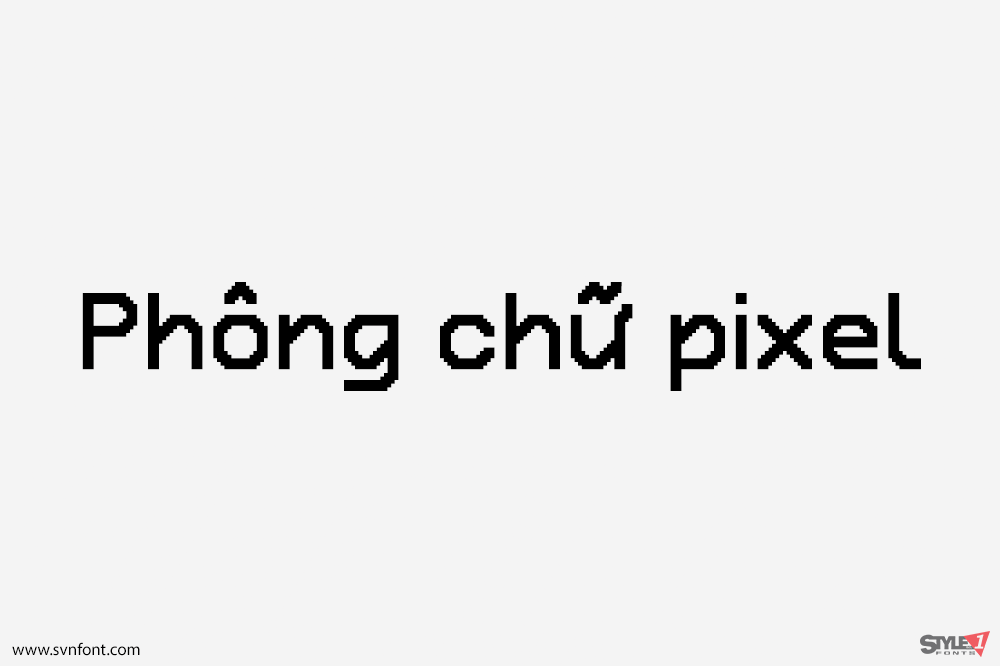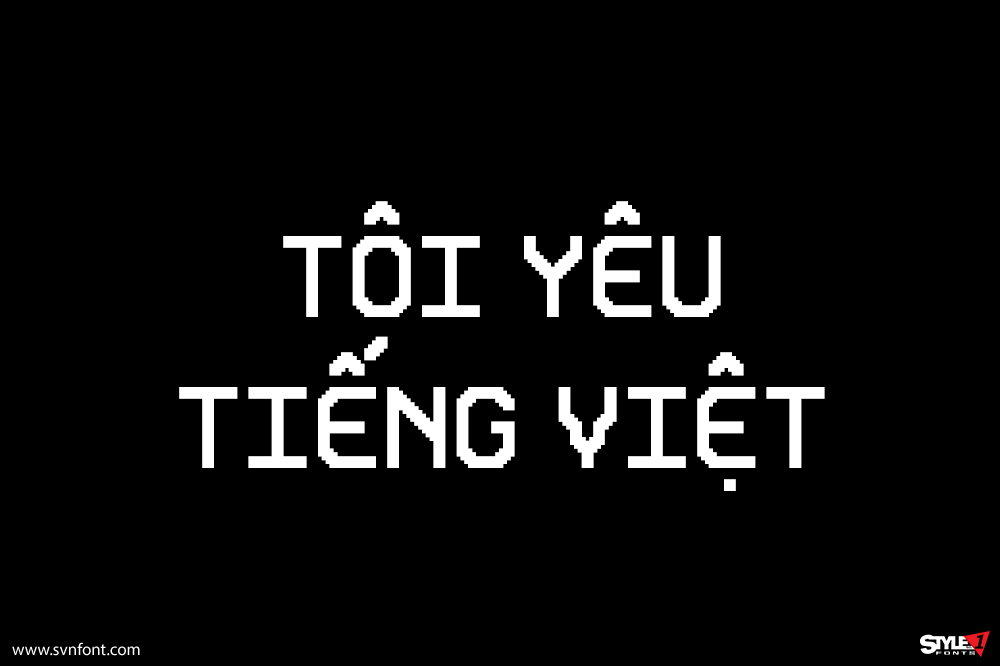
Retron 2000 là một font chữ dạng điểm ảnh (pixel) được thiết kế bởi Daymarius, font được cung cấp miễn phí cho mọi mục đích sử dụng. Retron 2000 thích hợp cho thiết kế về điện tử, trò chơi, bảng hiệu…
Nhà thiết kế: Daymarius
Nhà phát hành: Vasily Draigo aka Daymarius